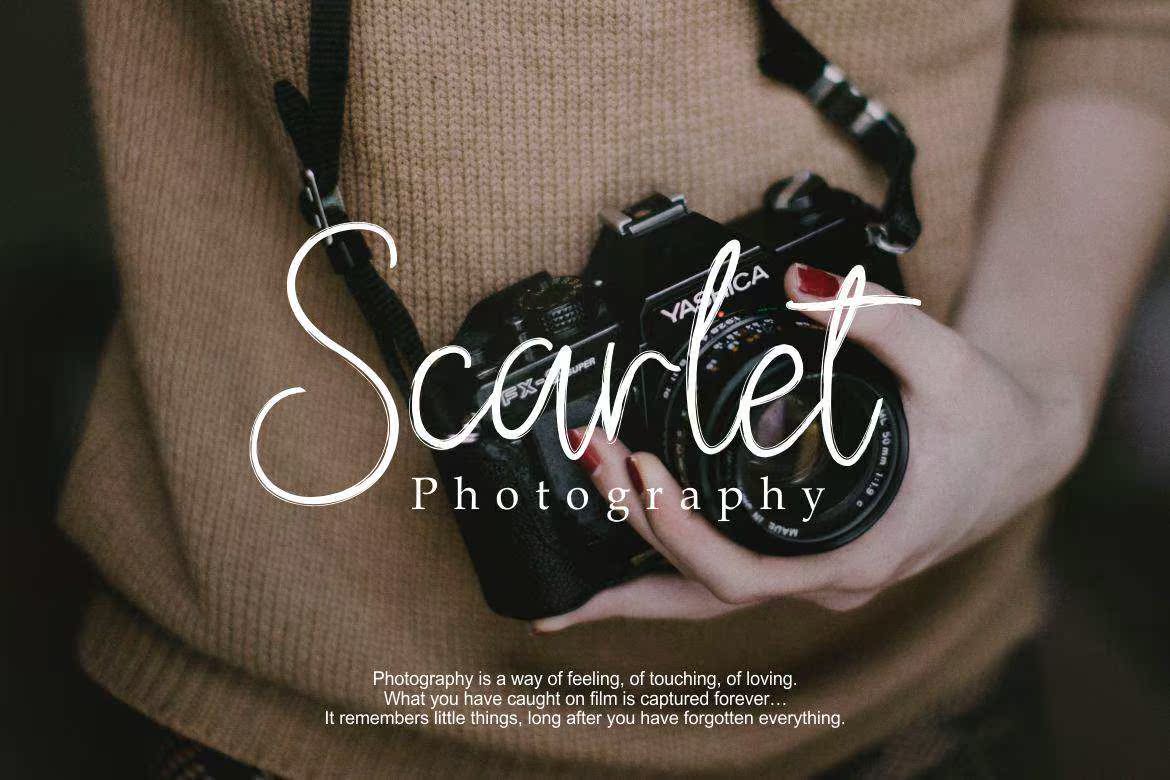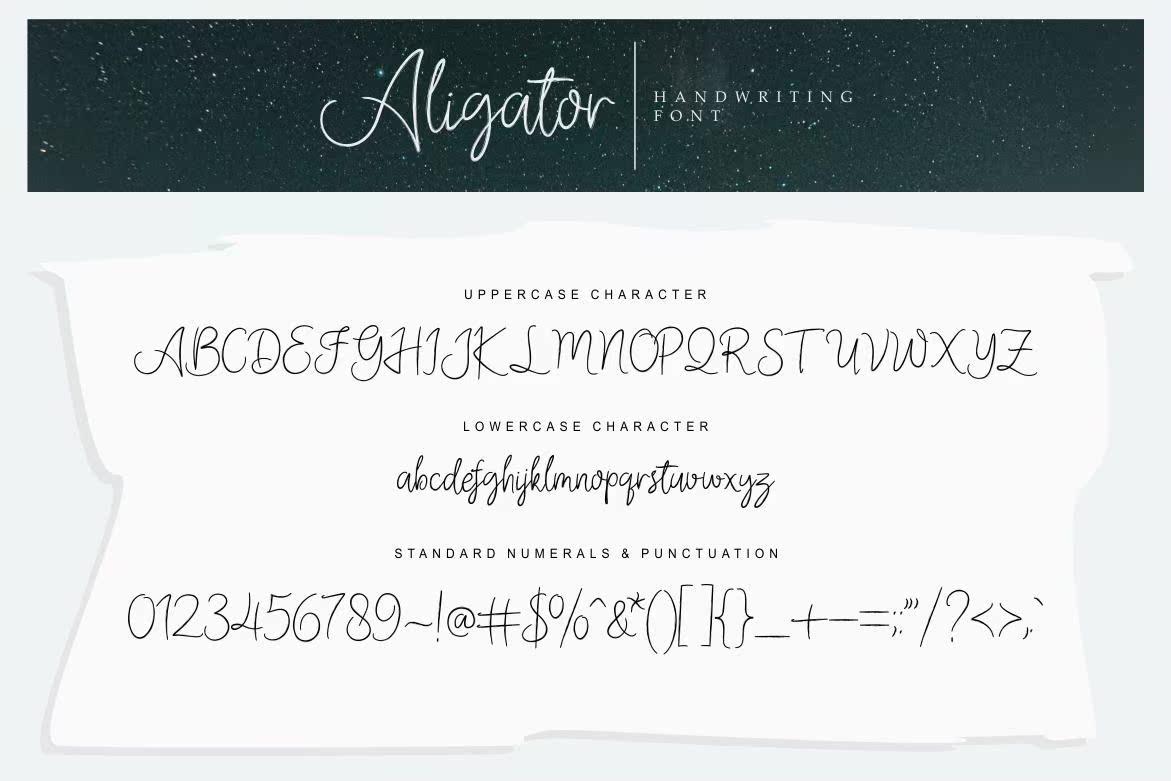
每个人都可以导入连字和书写字体。使用SubtleTexture使该字体更加优雅自然。该字体非常适合用于服装、品牌、杂志、海报、报价、名片和其他。Aligator字体包含以下连字:aa、ii、uu、ee、oo、st、ts、os、as、us、ns、is、ks、ms、yscs、ds、es、fs、gs、ls、qs、vs、ws、zs、ax、az、ll、ss,每个人都可以导入连字和书写字体。使用SubtleTexture使该字体更加优雅自然。该字体非常适合用于服装、品牌、杂志、海报、报价、名片和其他。Aligator字体包含以下连字:aa、ii、uu、ee、oo、st、ts、os、as、us、ns、is、ks、ms、yscs、ds、es、fs、gs、ls、qs、vs、ws、zs、ax、az、ll、ss、th